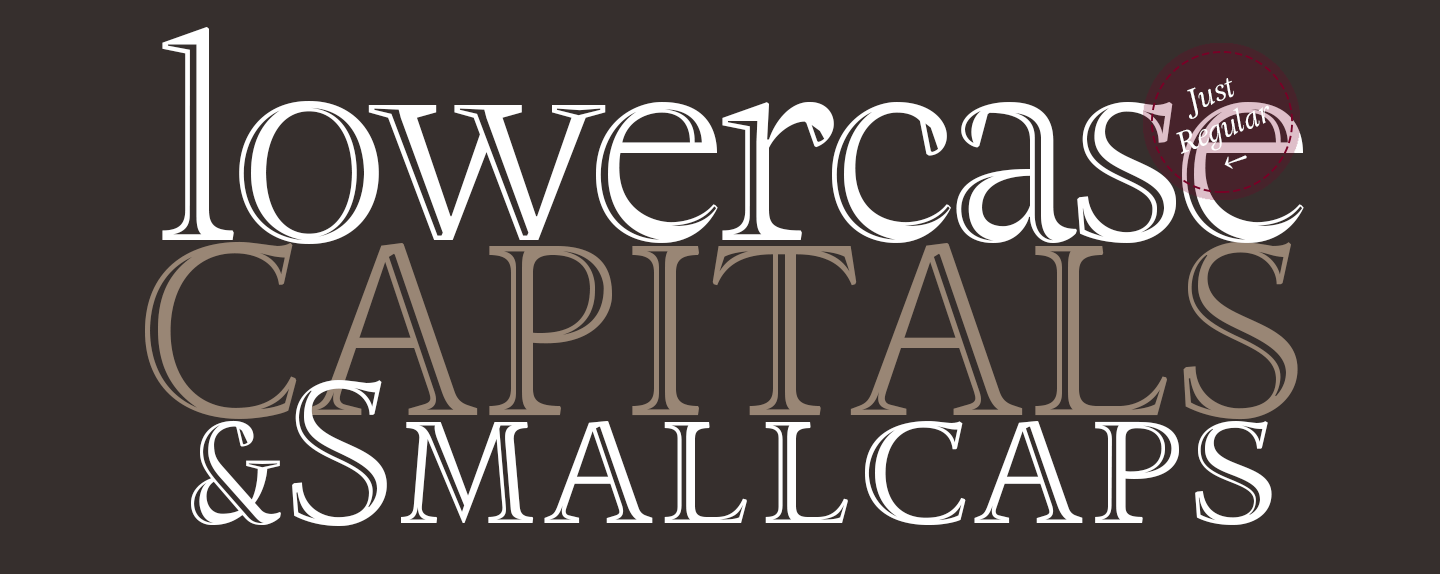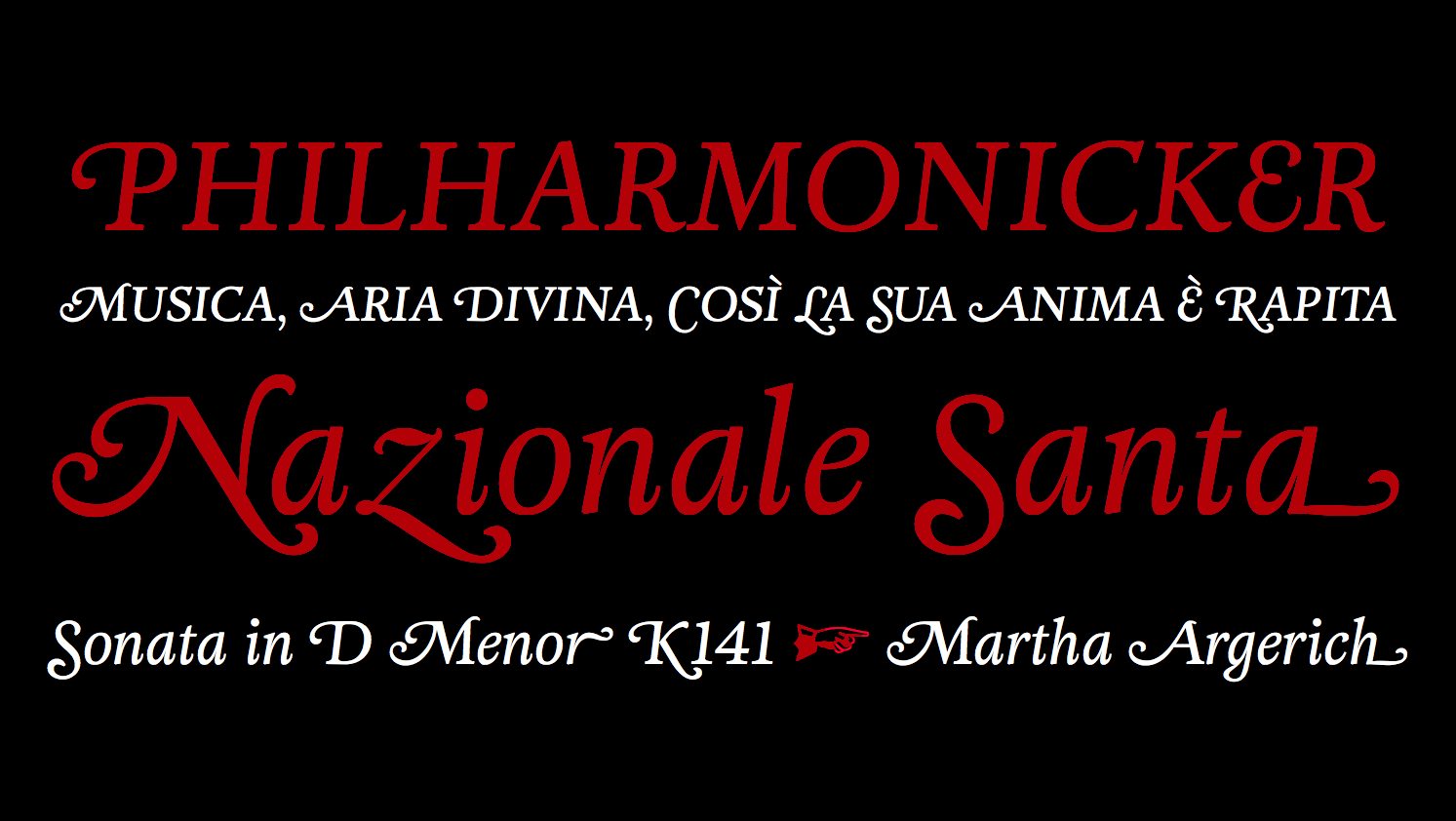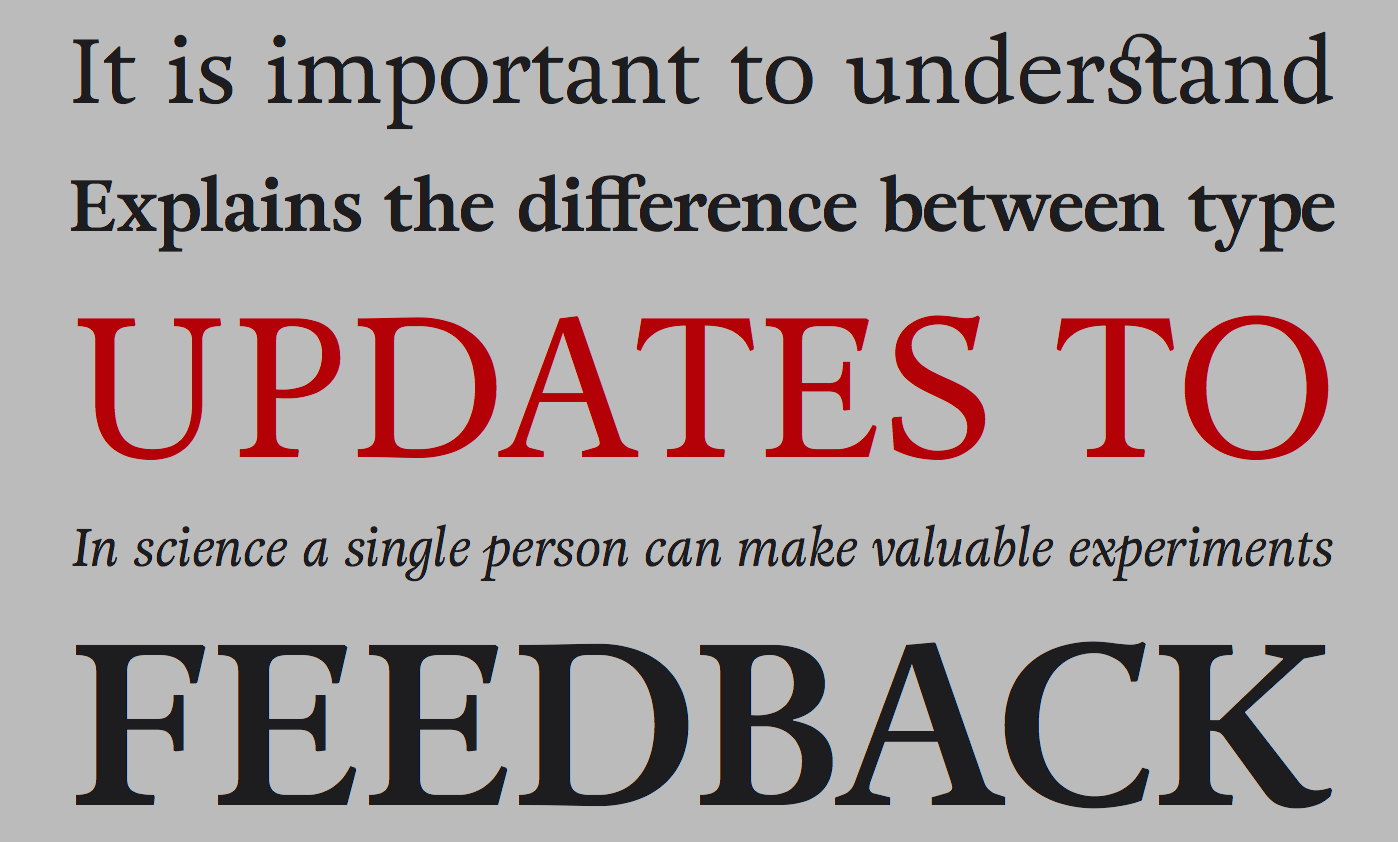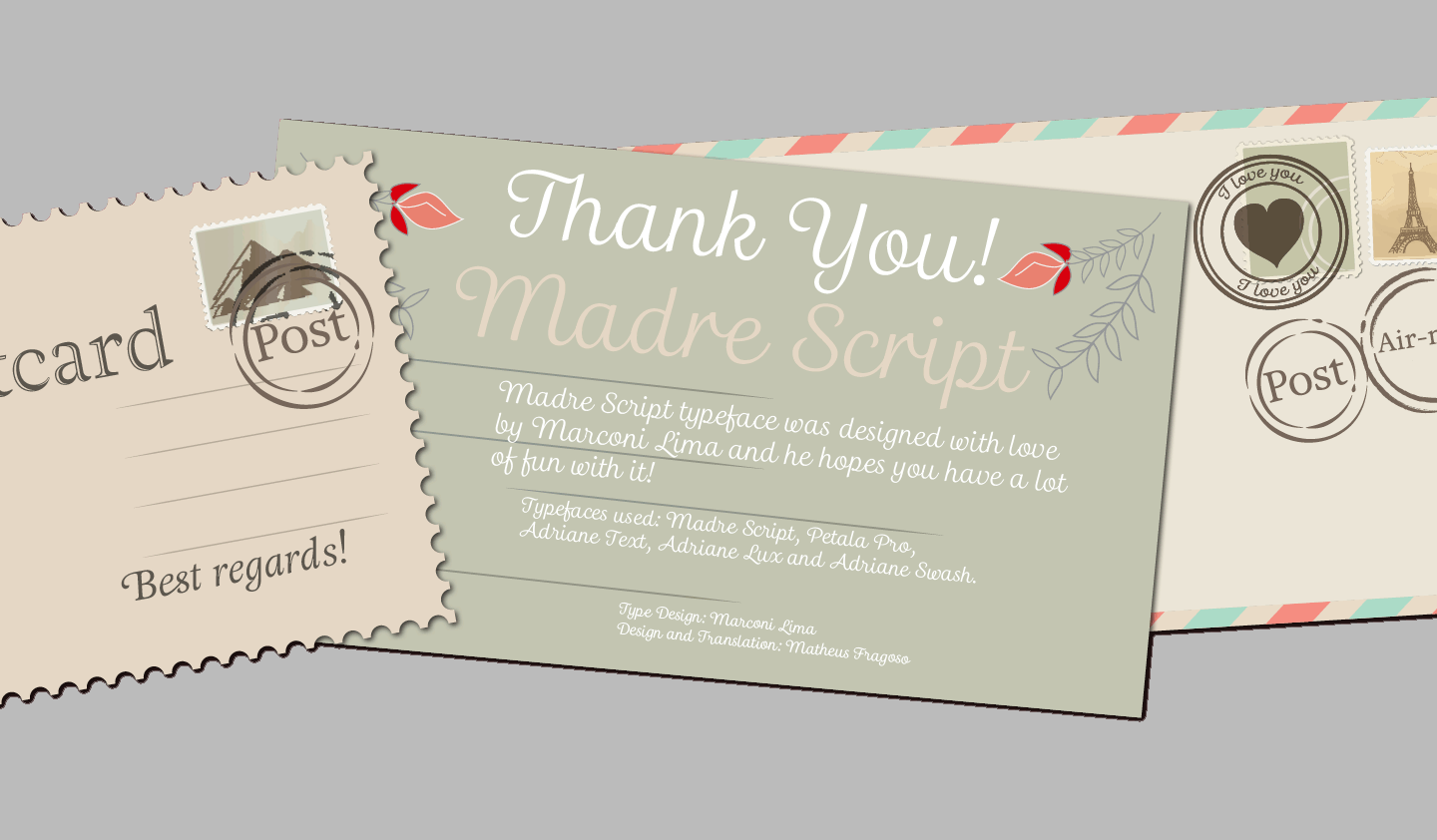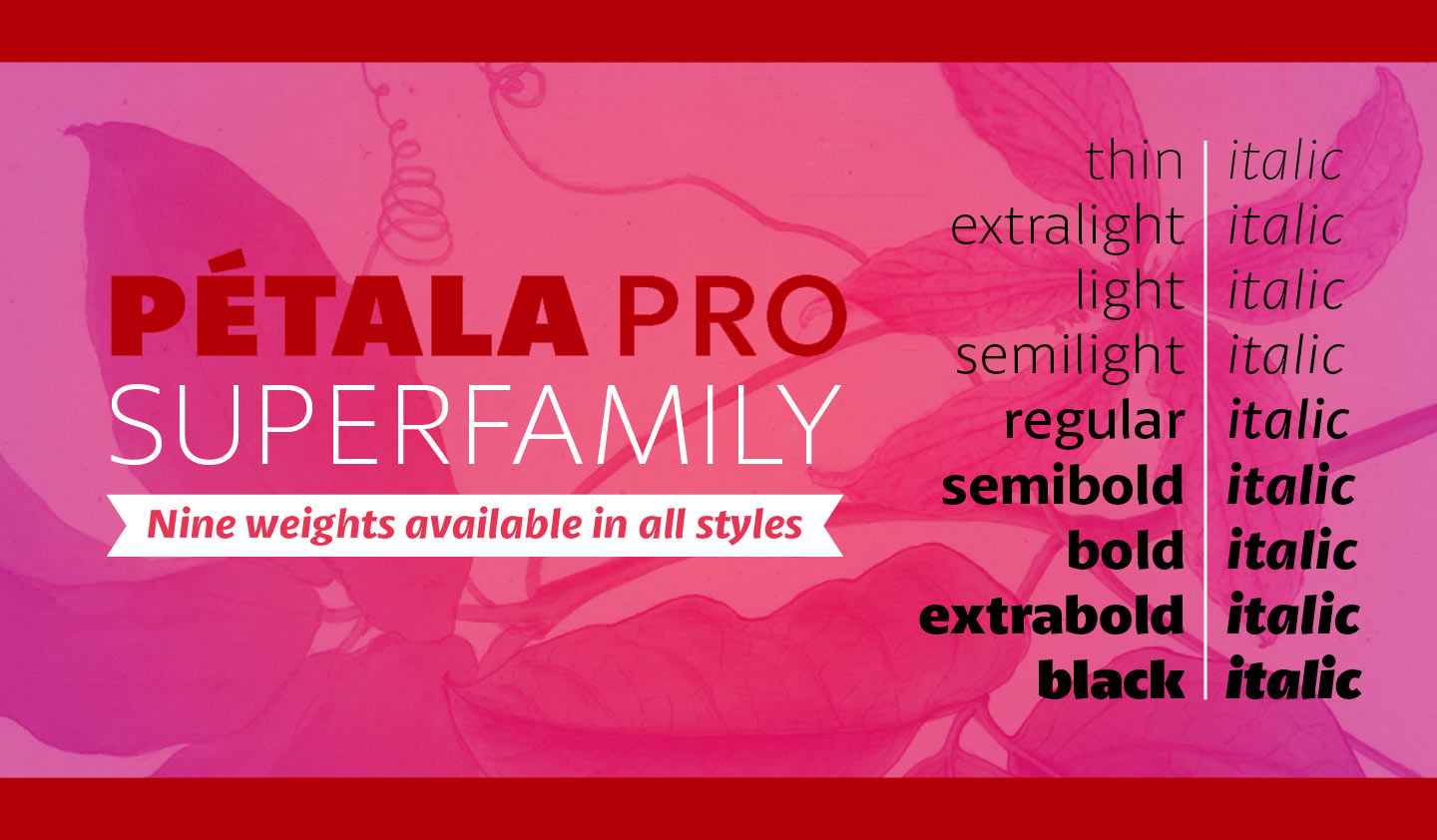
30 Tage Kunst im Orangelab, Berlin
30 Tage Kunst, eine Veranstaltung des Orangelab (Foto: Chloë Litchfield)
Zum fünften Mal findet in diesem November die Veranstaltungsreihe 30 Tage Kunst statt, im Orangelab, das seit 3 Jahren auch die Heimat des Creative Morning Berlin ist. Die Idee für das einmonatige Kunst-Event stammt vom Leiter des Orangelab, dem Schauspieler Hans Brückner. »Ursprünglich wollte ich in meiner Wohnung Lesungen im Stile der Salons des frühen 20sten Jahrhunderts anbieten.« erinnert sich Brückner an die erste Idee. Doch seine Wohnung war zu klein dafür. 2009 lernte er Marc Maximilian Doege kennen, der am Kurfürstendamm gerade die Galerie POPUP 195 eröffnet hatte. Und genau dort fand am 1. November 2009 die Premiere von 30 Tage Kunst statt: Hans Brückner trug Edgar Allan Poe vor, am Flügel begleitet von Marco Maria. Fotos von diesem Abend gibt es keine, aber einen Blogbeitrag von Hans Brückner …
Hans Brückner in seiner Spielstätte, dem Orangelab, wo er ab morgen 30 Tage Kunst anbietet (Foto: Robert Schatton)
Übermorgen, am Halloween-Freitag, startet also die fünfte Saison, mit einem Aufwärmabend unter dem launigen Motto: »Meet the artist in person. Stehrumchen mit Film.« Gezeigt werden die Film »Am Savignyplatz«, von Caterina Woj, und die 30-minütige Reportage »Von 6 bis 6 am Savignyplatz«. Im Programm heißt es: »Der Savignyplatz gehört den Bohemiens. Den Bildungsbürgern, Literaten, Künstlern und solchen, die sich dafür halten. Leute, die gern lange schlafen und spät ins Bett gehen. Lange ausharren. In den vielen guten Kneipen am Bermudadreieck der bürgerlichen Piazza. Zum Beispiel im ›Zwiebelfisch‹. … Hier ist die Zeit stehen geblieben. Die Stammgäste altern mit. Auch Zappa, der Kneipenkater, verbringt hier lange Nächte.«
Wenn der Verleger Klaus Wagenbach und der Chef des Buchhändlerkellers in der Carmerstrasse über ihren geliebten Platz erzählen, gibt es viel zu schmunzeln. Und zu lernen. Über die berüchtigten 70er Jahre. Wie das alles hier einmal war. Beide Filme vermitteln ein Bild vom Savignyplatz, das viele Altberliner vergessen haben und Neuberliner noch nicht kennen. Künstler und Verleger, Literaten und Schauspieler erzählen und führen in ihre Welt. Der Eintritt ist frei.
Am Samstag erwartet uns eine Veranstaltung, die auch bei Grafikern und Editorial-Designern auf Interesse stoßen sollte. Es geht um die Zeitschrift »Das Magazin«, und die Devise lautet: 90-60-90 – ein maßloser Abend mit dem Magazin. Die einen nennen das Heft »New Yorker des Ostens«, die anderen eine monatliche Wundertüte. Gegründet 1924, erfindet sich Das Magazin immer wieder neu und hat mit seiner ungewöhnlichen Mischung aus Journalismus und Literatur seit Jahrzehnten Erfolg.
Viel Platz, zentrale Lage, angenehme Atmosphäre: Das Orangelab, auch die Heimat des Creative Morning Berlin (Foto: Fabian Hamacher)
Am ersten »amtlichen« Abend von 30 Tage Kunst erzählen die Macher des Magazins Stories und Skurriles aus 90 Jahren Redaktionsarbeit. Hierzu begrüßt Hans Brückner Pierre Sanoussi-Bliss und Franziska Arnold, sowie die Magazin-Kolumnisten Kirsten Fuchs und Stefan Schwarz. Es singt Pascal von Wroblewsky. Eintritt: 12,50 €.
Typofolio – Fonts mit Leidenschaft aus Amazonien
Marconi Gomes Lima strebt nach Perfektion. Zwei Kriterien kennzeichnen seine Entwürfe. Lima feilt und tüftelt sowohl zeichnerisch als auch technisch auf hohem Niveau.
Limas Schriften gemein ist die begeisterte Besessenheit mit der ihr Schöpfer seiner Profession nachgeht: ausgefallene Konzepte, sorgfältige Formgebung, balancierte Kontraste und nicht zuletzt ein prall gefüllter Zeichenvorrat. Als der Woche bieten wir für kurze Zeit alle Schriften von Typefolio mit einem Rabatt von 30% an.
Zu den Schriften: Zwei Entwurfsmodelle verbinden Madre Script, die Konstanz der Form zum Einen, zum Anderen die Freiheit der Schreibschrift. Dazwischen bewegt sich mit vielfältigen Zeichenverbindungen und raffinierten, sehr senkrechten Schwüngen die vielseitige Madre-Schreibschrift im Print- und Web-Format. Die OpenType-Feature Menüs ‘Contextual Alternates – calt’ und ‘Ligatures – liga’ sorgen für die präzise Steuerung von Alternativ-Zeichen und Verbindungen.
Madre Script ist ein ein technisch ausgeklügelter und gut gelaunter Script-Allrounder für alle gestalterischen Situationen, die nach Persönlichckeit, Charme und Wärme verlangen: Verpackungen, Anzeigen, Branding, Headlines …
Adriane ist eine Sippe. Von Sippen statt von Familien reden wir, wenn ein Schriftsystem mehrere Schriftklassen abdeckt. Die Kernfamilie mit den vier Grundschnitten Regular und Bold, sowie passenden Kursiven entstand von 2006 bis 2007. Als Textfamilie mit hoher X-Achse für optimale Lesbarkeit ausgerichtet, überrascht sie mit ausgefallenen Details.
Wie alle Fonts von Marconi Lima überzeugt Adriane Text mit einem enormen Zeichenvorrat aus Small Caps, vier Ziffernsätzen (Tabellen- und Proportional- Ziffern, je mediäval und versal), zahlreiche Ligaturen für verschiedene Buchstaben-Kombinationen und zusätzlich Ornamente, Dingbats und Ampersands.
Adriane Text, gezeichnet für den Mengensatz, bleibt auch in kleinen Größen bestens lesbar. Der Fluss der Kursiven setzt einen zusätzlichen Akzent.
Adriane Swash ist ist der schwungvolle Display-Vertreter der Sippe. Basierend auf der Formensprache der Text-Familie, verhilft sie Überschriften und Auszeichnungstexten zu einem klassisch-glamorösen Auftritt. der Swash-Schnitt enthält Versalien, Small Caps und Minuskeln. Die Schwungbuchstaben werden im OpenType-Menü aktiviert. Dort können auch Initale, Mittel- und Abschluss-Zeichen angewälht werden, sowie eine große Palette zusätzlicher Zeichen, wie Alternates, Ornamente und fremdsprachige Zeichen.
Wer es weniger düster mag und Leser nicht bereits mit der Headline verschrecken möchte, dem sei die Liste der Scary Type Comic-Fonts von FontFeed-Autor Yves Peters empfohlen.